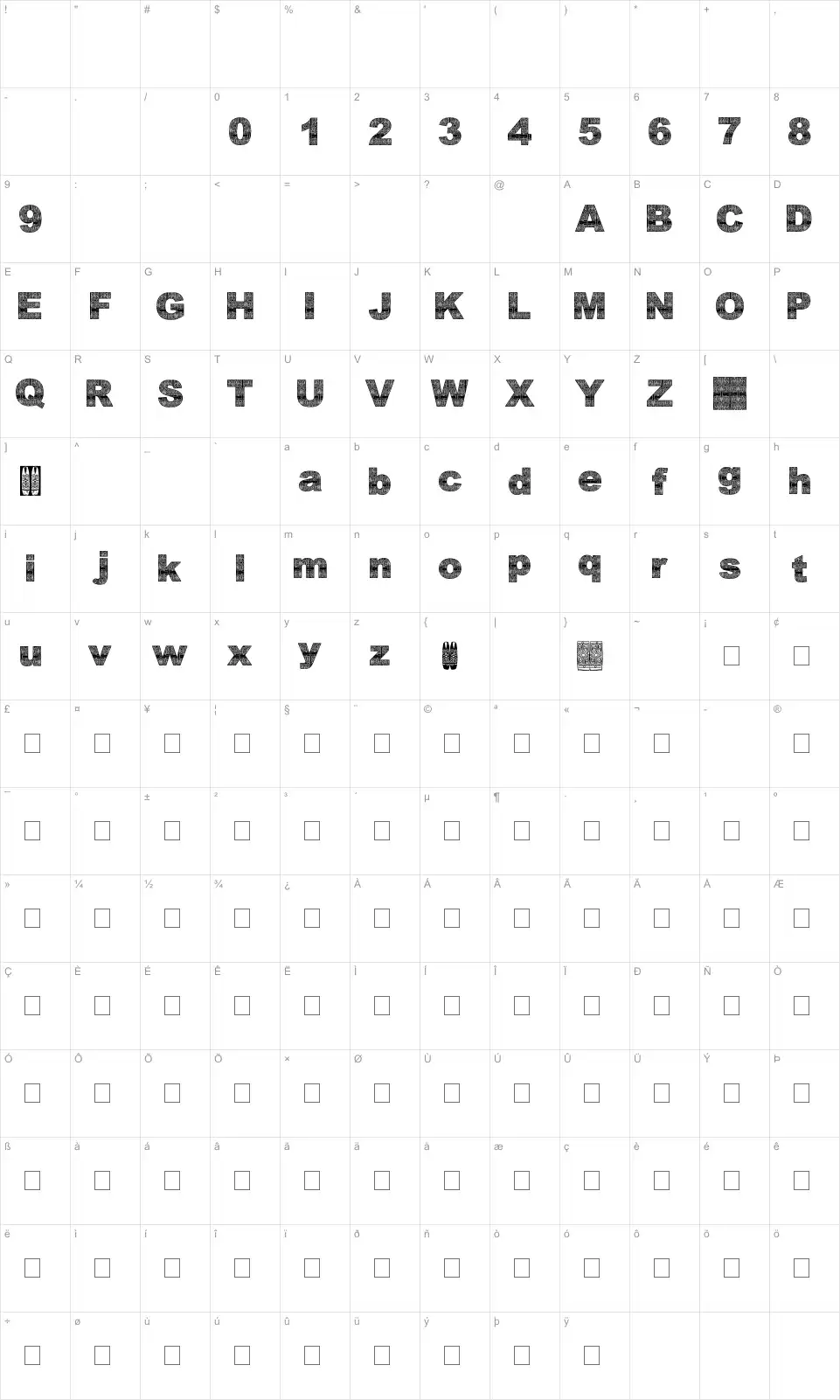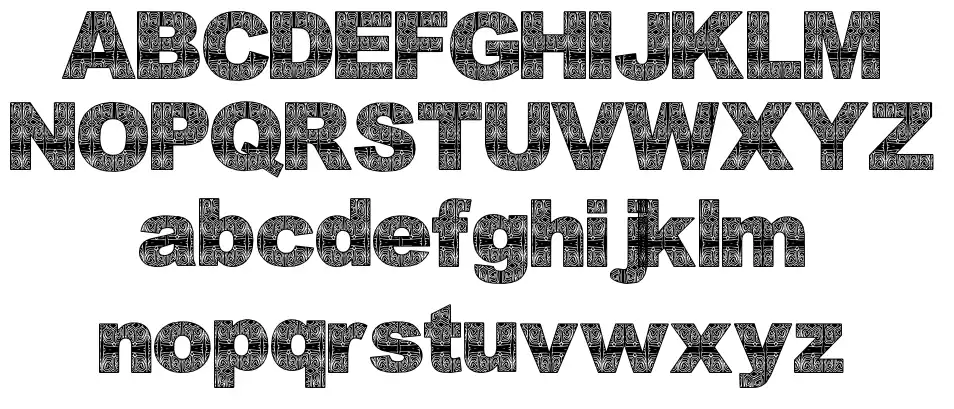
Asmat Font 2007 – Fonte Grátis
Asmat Font 2007
A Asmat Font 2007 é uma fonte fantasia criada pela Asia Culture, uma fonte elegante e divertida que pode transformar qualquer texto em um design único e sofisticado. Esta fonte, que você pode adquirir de forma gratuita, é perfeita para adicionar um toque especial em seus projetos digitais. Com sua categoria Fancy e Decorative, a Asmat Font 2007 é a escolha ideal para aqueles que desejam dar um novo charme às suas criações. Licenciada como Donationware, o formato TTF permite que você instale a fonte em seu computador e use-a sem limitações. Adicionada em 13 de julho de 2022, a Asmat Font 2007 já foi baixada mais de 6799 vezes, o que prova sua popularidade. A fonte é ideal tanto para designers de sites quanto para profissionais que criam materiais publicitários ou editoriais, garantindo um visual atraente e único. Para experimentar a Asmat Font 2007, é fácil gerar um preview personalizado, o que permite que você veja como ela vai se assemelhar ao seu documento antes de aplicar. Com seu tamanho de apenas 282 KB, a Asmat Font 2007 não ocupará muito espaço em seu sistema e pode ser facilmente instalada para uso contínuo. Para mais informações, o designer pode ser contatado através do site www.asia-culture.blogspot.com.
Mapa de caracteres da fonte Asmat Font 2007